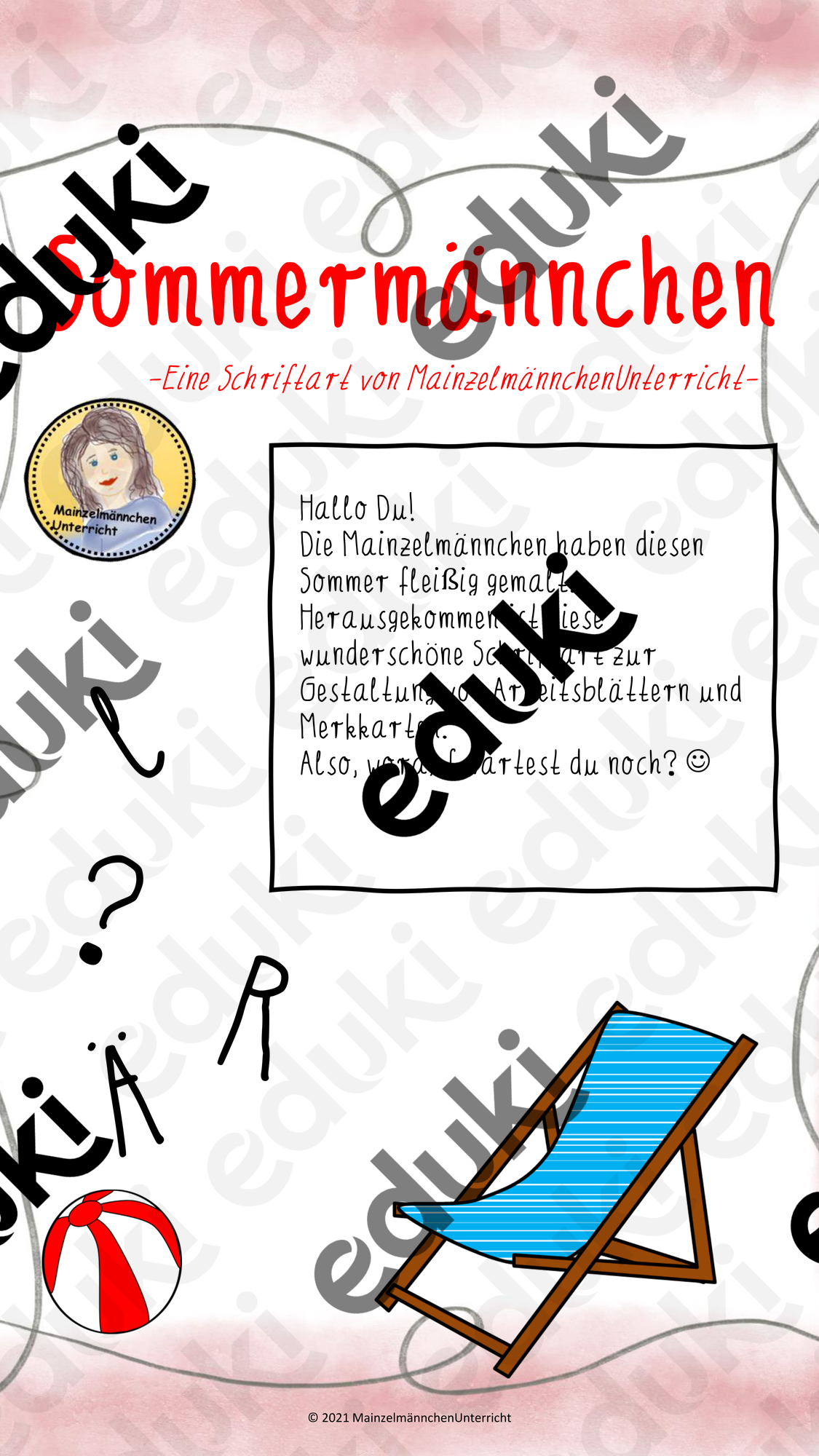
selbst erstellte Schriftarten - Sommermännchen Font - MainzelmännchenUnterricht - Deckblatt
Anbei meine lockere und sommerliche Schrift Sommermännchen mit Umlauten, Groß- und Kleinbuchstaben und den wichtigsten Satzzeichen.
Sommermännchen Font